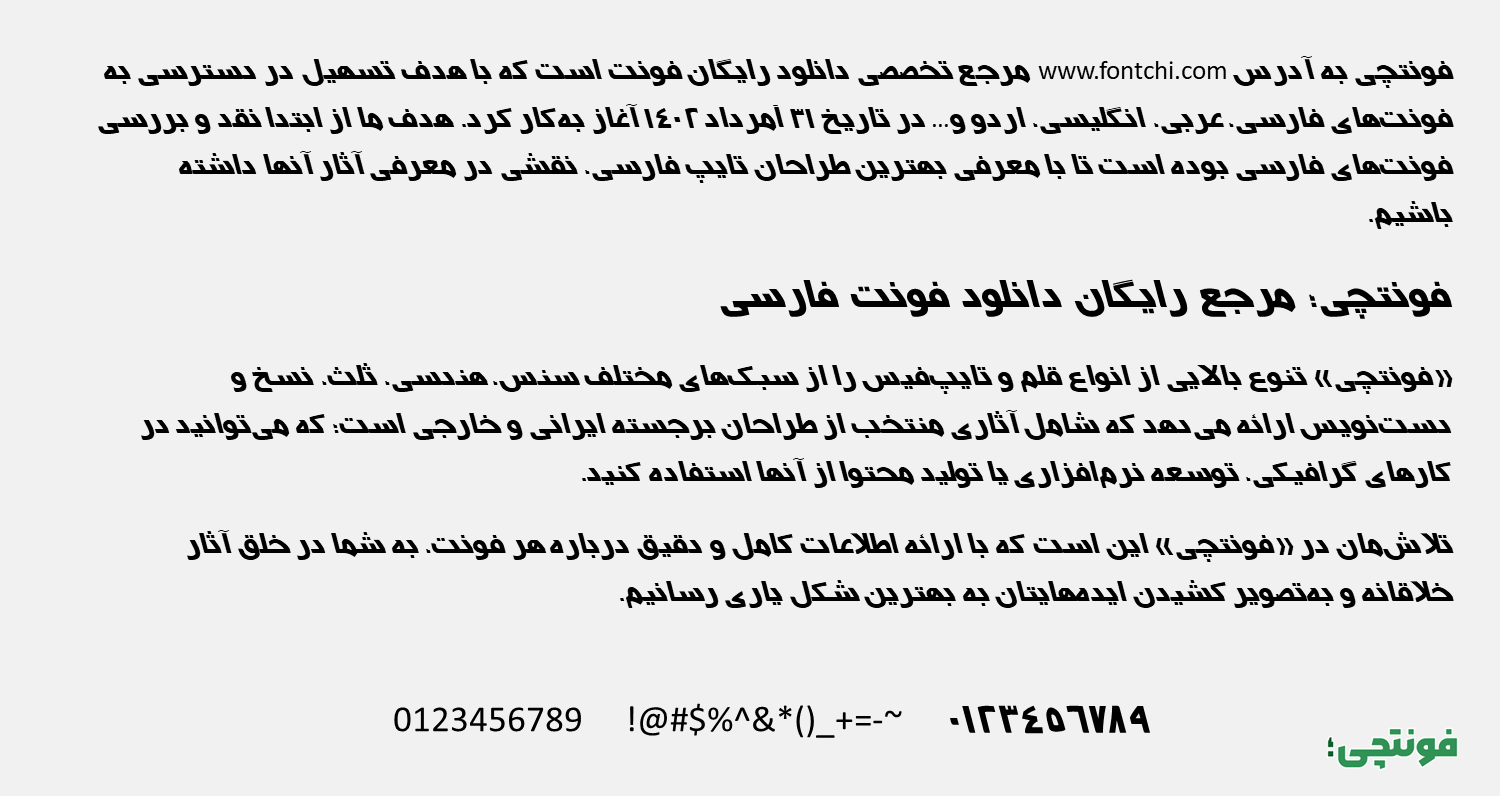
فونت بی نسیم (B Nasim)
فونت بی نسیم (به انگلیسی: B Nasim) قلمی با طراحی به سبک نسخ است که در دهه هفتاد طراحی و تولید شده است. با ساختاری که این قلم دارد میتواند برای فونت عناوین و استفاده در فضاهای تبلیغاتی و گرافیکی مناسب باشد. در ادامه به لینک دانلود فونت بی نسیم در سایت فونتچی دسترسی خواهید داشت.
اگر به دنبال یک فونت بولد و ضخیم هستید، قطعا فونت بی نسیم میتواند یکی از انتخابهای پرطرفدار باشد. این فونت علاوه بر وزن ضخیمی که دارد، دارای طراحی به سبک ایتالیک است که موجب نمایشیتر شدن نوشتههای شما، خصوصا در فضاهای تبلیغاتی خواهد شد.
در ادامه این نوشته از سایت فونتچی به بررسی دقیقتر فونت b nasim خواهیم پرداخت؛ قلمی که جدای از ویژگیهای مرسوم، از ویژگی OutLine نیز پشتیبانی میکند که میتوانید به کمک نرمافزارهایی نظیر فتوشاپ، اینشات و کپ کات از این ویژگی برای نوشتههای خود استفاده کنید.
پیش نمایش و وزن فونت بی نسیم (B Nasim)
قلم بی نسیم دارای طراحی به سبک ایتالیک است که با وزن Bold ساخته شده است. این سبک خاص ایتالیک کردن فونت در دهههای هفتاد در کمتر فونت فارسی وجود داشت؛ کلیه حروف علاوه بر ساختار ایتالیک، دارای ظاهری استوار و نسبتا قائم هستند که ظاهر جدی به فونت داده است.
چنین ساختاری برای استفاده در عناوین مناسب است؛ خواه استفاده در فضاهای تبلیغاتی مثل بیلبوردها، بنرهای تبلیغاتی یا فونت تامنیل برای پست شبکههای اجتماعی باشد خواه اینکه از آن به عنوان فونت جلد کتاب و مجله استفاده کنید.
مهمترین مسئلهای که برای استفاده از فونت بی نسیم وجود دارد این است؛ این قلم را با اندازه درشت استفاده کنید! چرا که در ابعاد بزرگتر ظاهر آن نمایشیتر میشود و خود را بهتر نشان خواهد داد. از همینرو برای استفاده در متون طولانی مناسب نیست و بیشتر برای عناوین و متنهای کوتاه کاربردی خواهد بود.
فونت فارسی بی نسیم از این زبان پشتیبانی نسبتا کاملی دارد و تنها موردی که شاید بهعنوان ضعف از آن یاد شود، عدم استفاده از اعداد فارسی «۴۵۶» در این قلم است. شاید دلیل اینکه طراح از اعداد عربی «٤٥٦» استفاده کرده مربوط به ساختار نسخ قلم بوده باشد یا اینکه در دهه هفتاد، زیاد مسئله مهمی نبوده است.
با اینحال این قلم از زبان عربی نیز در حدی که فقط حروف مشترک با فارسی داشته باشد پشتیبانی میکند. گلیفهایی نظیر «ك، ؤ، ئ» عربی که در فارسی کاربردی ندارند در این فونت وجود ندارد. زبانهای لاتین چه در بخش اعداد، چه حروف و چه کاراکترهای خاص در این فونت فاقد گلیف بوده و از فونت پیشفرض سیستمعامل مانند تصویر بالا استفاده میشود.
یکی دیگر از کاربردهای محبوبی که این فونت خصوصا در دهه ۸۰ داشته است، در صنعت چاپ و مطبوعات بود که بهوفور مورد استفاده قرار میگرفت. بهدلیل وزن بولد فونت بی نسیم و از طرف دیگر ساختار کلی ایتالیک این قلم، در چنین صنعتی موجب جلب توجه بیشتر میشد که باعث خوانش بیشتر جراید، کتب و روزنامهها را بهدنبال داشته است.